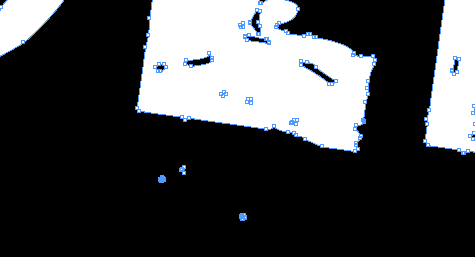
Schrift in Pfad umgewandelt, jetzt einzelne Pfade bearbeiten
ich hab in InDesign mit der VTKS Distress gearbeitet. Diese stark "verrottete" Schriftart hat überall noch kleine Punkte (wie Frabkleckser, siehe Screenshot) um die einzelnen Buchstaben, die ich gerne entfernen würde. Also hab ich die Schrift in Pfade umgewandelt und dachte, das ich wie beim Illustrator jetzt diese störenden Farbkleckse (ich nenn die jetzt so) mit dem weißen Pfeil mrkieren und entfernen kann. Allerdings markiert mir der weiße Pfeil nich die einzelenen Pfade, sondern den gesamten Pfad des Schriftzugs (siehe Screenshot). In Illustrator kann ich die Pfade bequem voneinander trennen um einzelne Sachen zu bearbeiten, aber in Indesign finde ich nichts passendes.
Du könntest den verknüpften Pfad lösen, dann kannst du einzelne Bestandteile löschen. Musst halt Punzen wieder verknüpfen. Oder – was an der Stelle eleganter ist – du ziehst mit dem Direktauswahl-Werkzeug (weißer Pfeil) jeweils eine Auswahl und löschst diese, dann musst du verknüpfte Pfade vorher nicht auflösen.
halte die Alttaste gedrückt, dann kannst du mit dem weißen Pfeil einen kompletten Pfadbestandteil markieren.